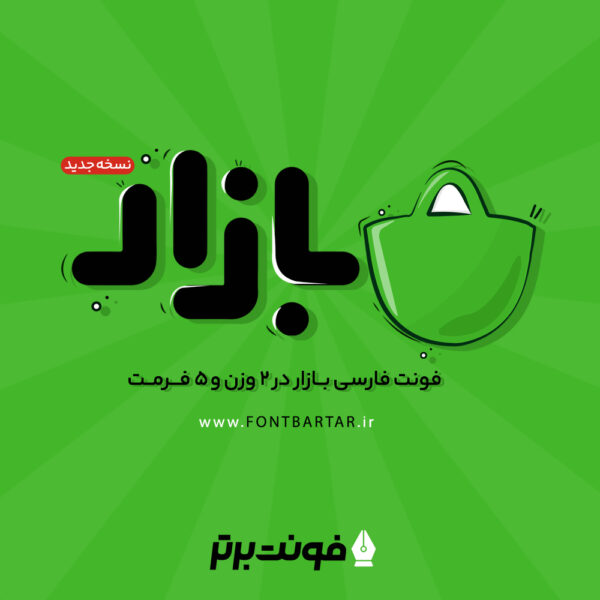
فونت فارسی بازار
فونت فارسی بازار این فونت زیبا که با الهام برداری از لوگو تایپ کافه بازار طراحی شده است این فونت حرفه ای در عین حال ساده می باشد که طراحان گرافیک و وب می توانند در انواع طرح های خود استفاده کنند.
شاید کمتر کسی وجود داشته باشد که با اپلیکیشن کافه بازار آشنا نباشد. کافه بازار یک فروشگاه نرم افزار اندروید است که توسط تعدادی از دانشجویان دانشگاه شریف طراحی شده و در مدت زمان کم به یکی از محبوبترین اپلیکیشن های اندرویدی برای مردم ایران تبدیل شد.
فونت بازار دارای چند وزن است؟
- این فونت در دو وزن سبک و سنگین می باشد.
فونت بازار از چه زبان هایی پشتیبانی می کند؟
- از دو زبان فارسی و انگلیسی را پشتیبانی می کند.
در طراحی فونت کافه بازار سعی شده تا مشابه لوگوی اپلیکیشن کافه بازار ساخته شود که ایده آل برای تبلیغات، لوگو، نام تجاری و صنایع خلاق، پوستر و بیلبوردها باشد.این فونت به صورت دو وزن Bold و Regular طراحی شده است که علاوه بر تمام حروف و اعداد فارسی، از همه حروف لاتین در شکل و سایز متناسب پشتیبانی میکند و هنگام قرارگیری این دو تایپ در کنار یکدیگر زیبایی خاصی به وجود می آید.
نسخه جدید فونت بازار چه تغیراتی کرده است:
- اضافه شدن وزن جدید نسخه 2
- بهبود ساختاری حروف نسخه 2
- رفع باگ های گذارش شده نسخه 2
- مشابه فونت لوگو تایپ کافه بازار
- طراحی آسان لوگوتایپ در زمان محدود
- انعطاف پذیر و قابل استفاده در هر طرحی